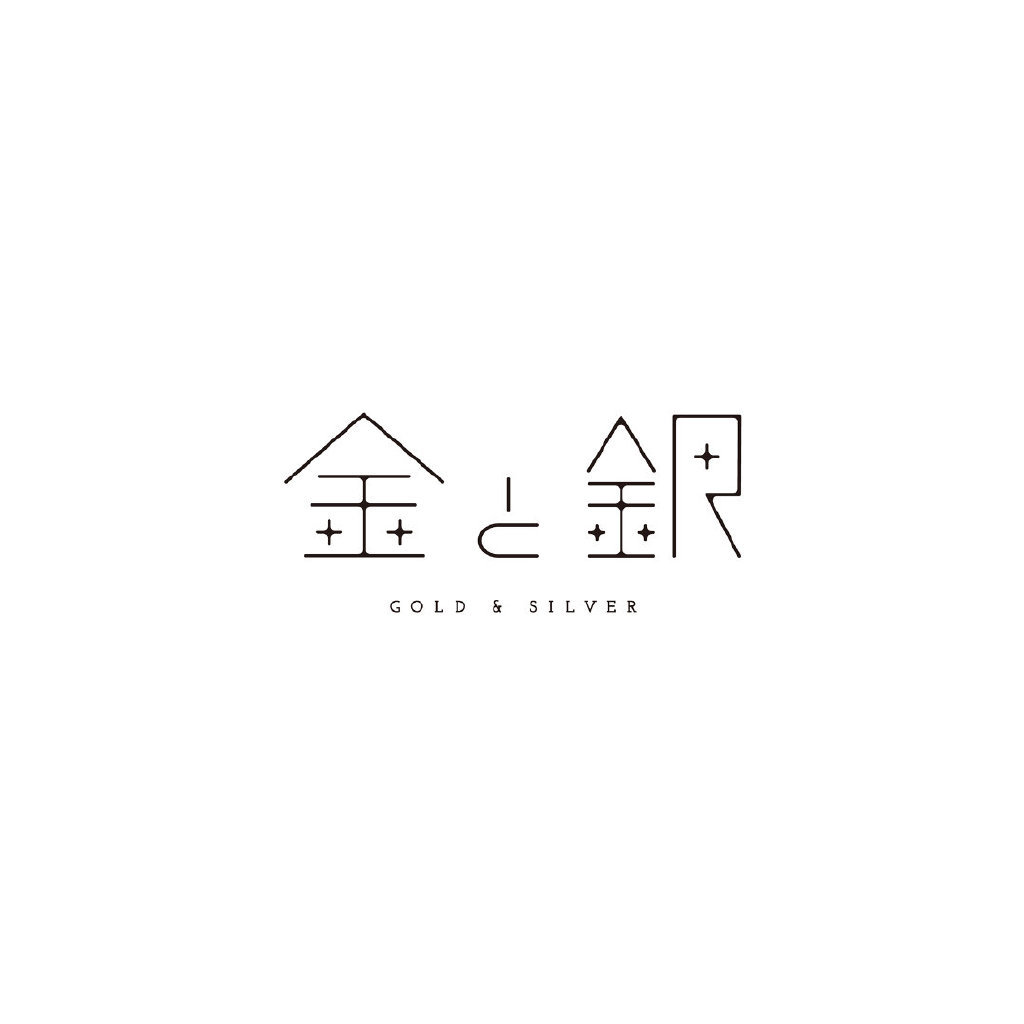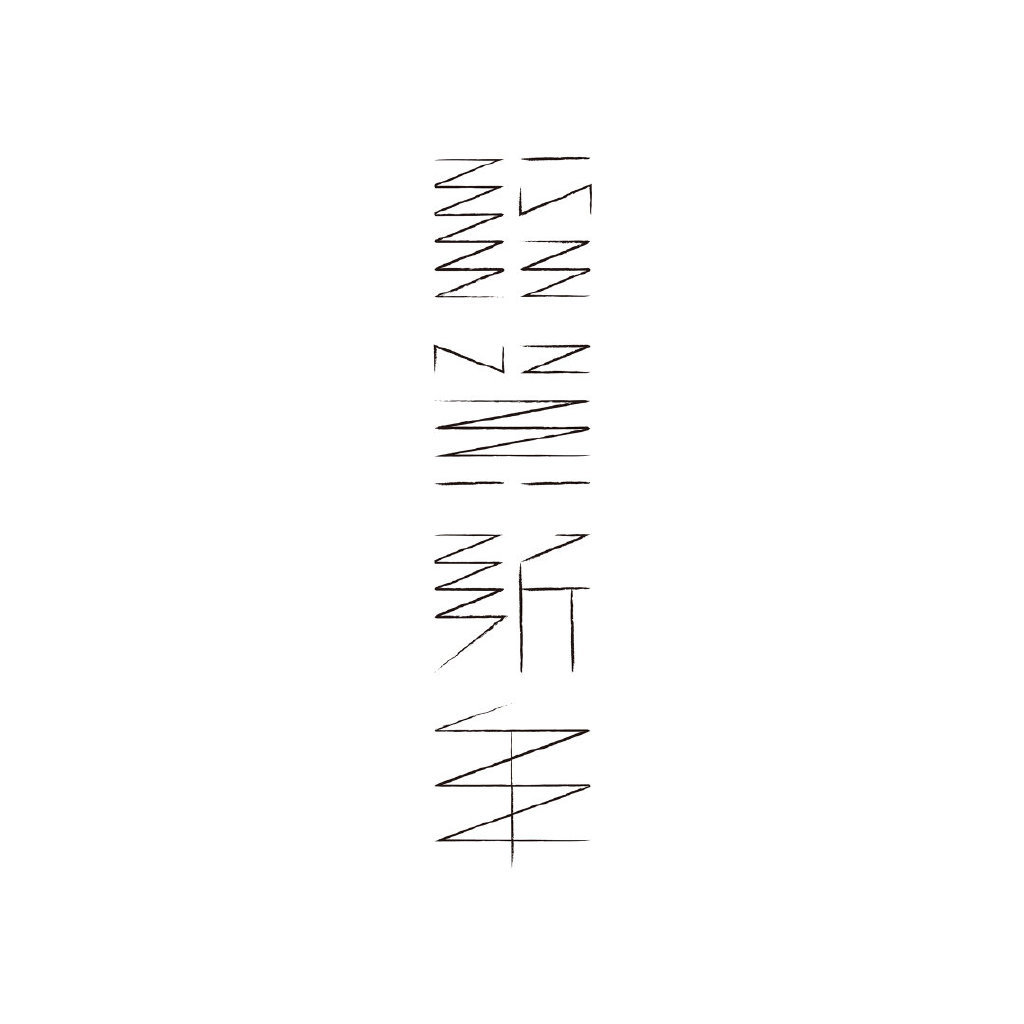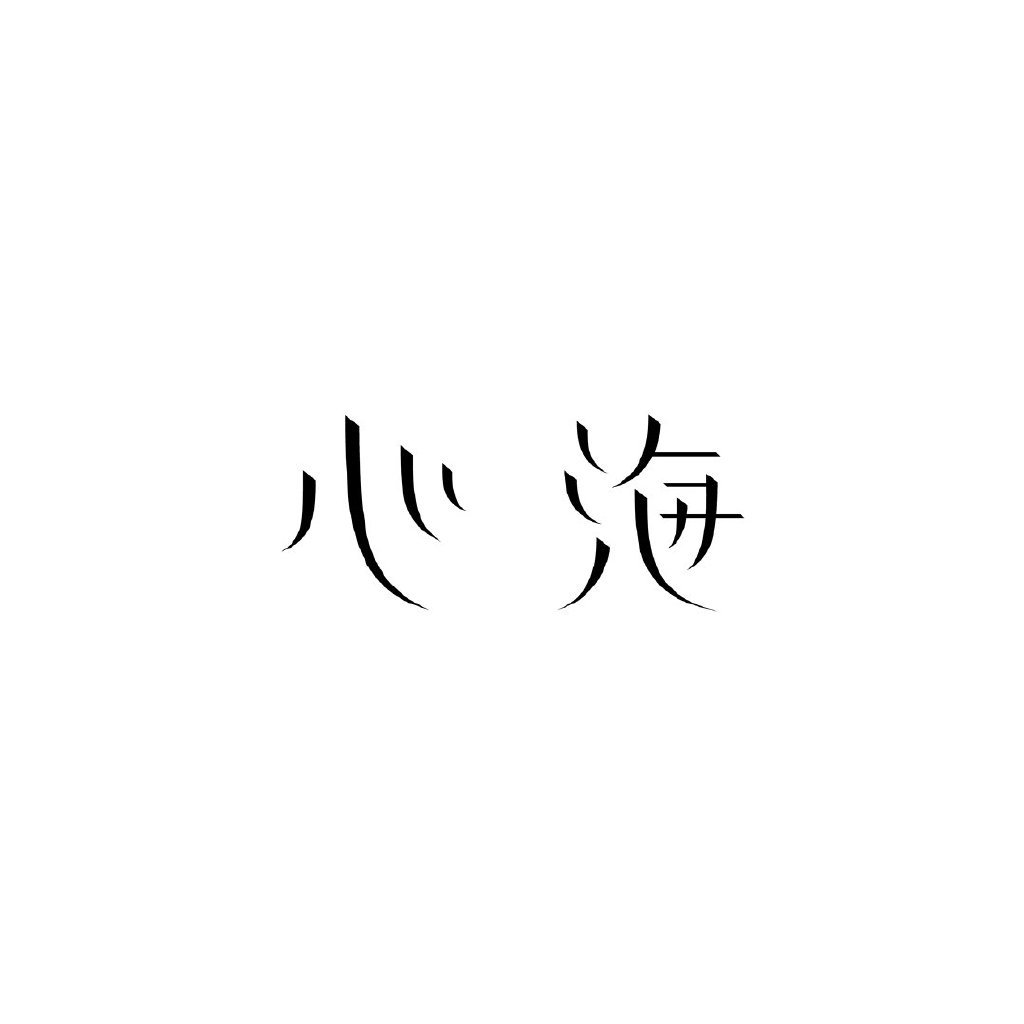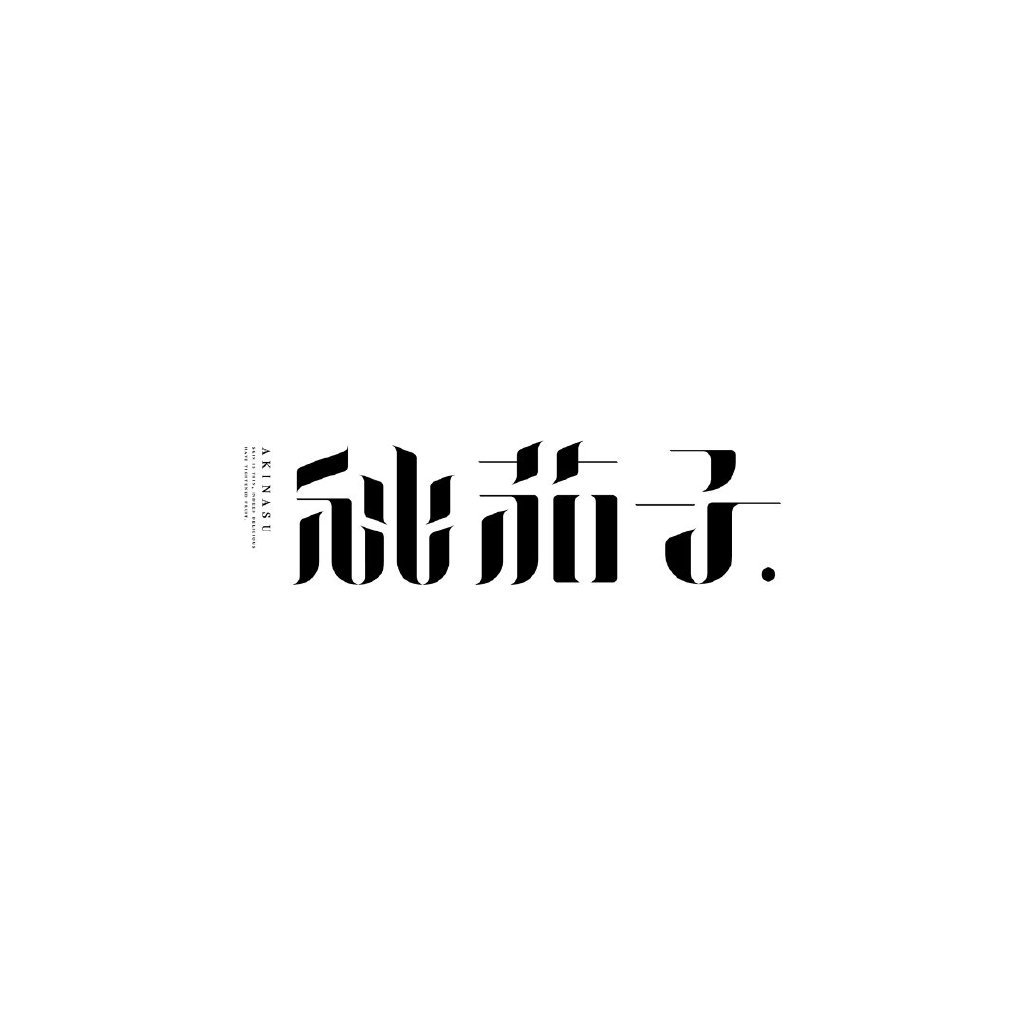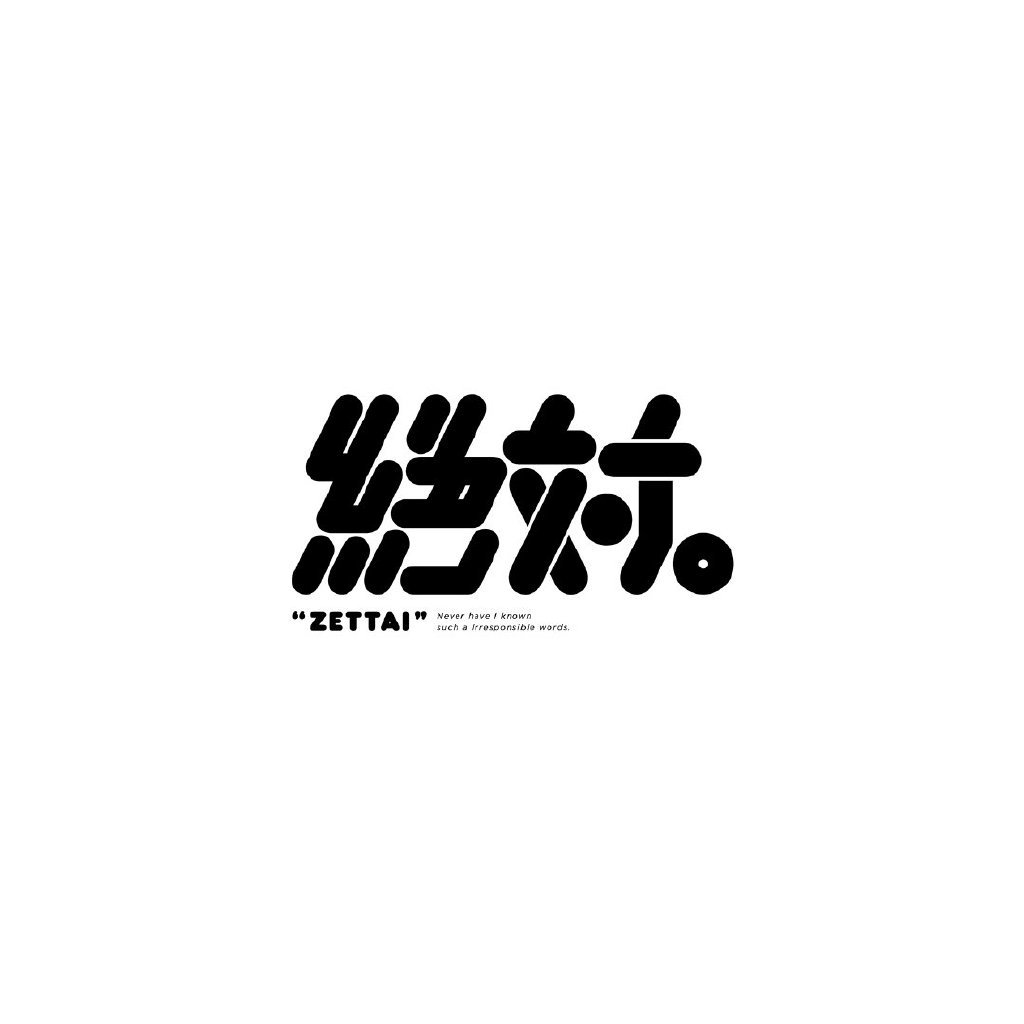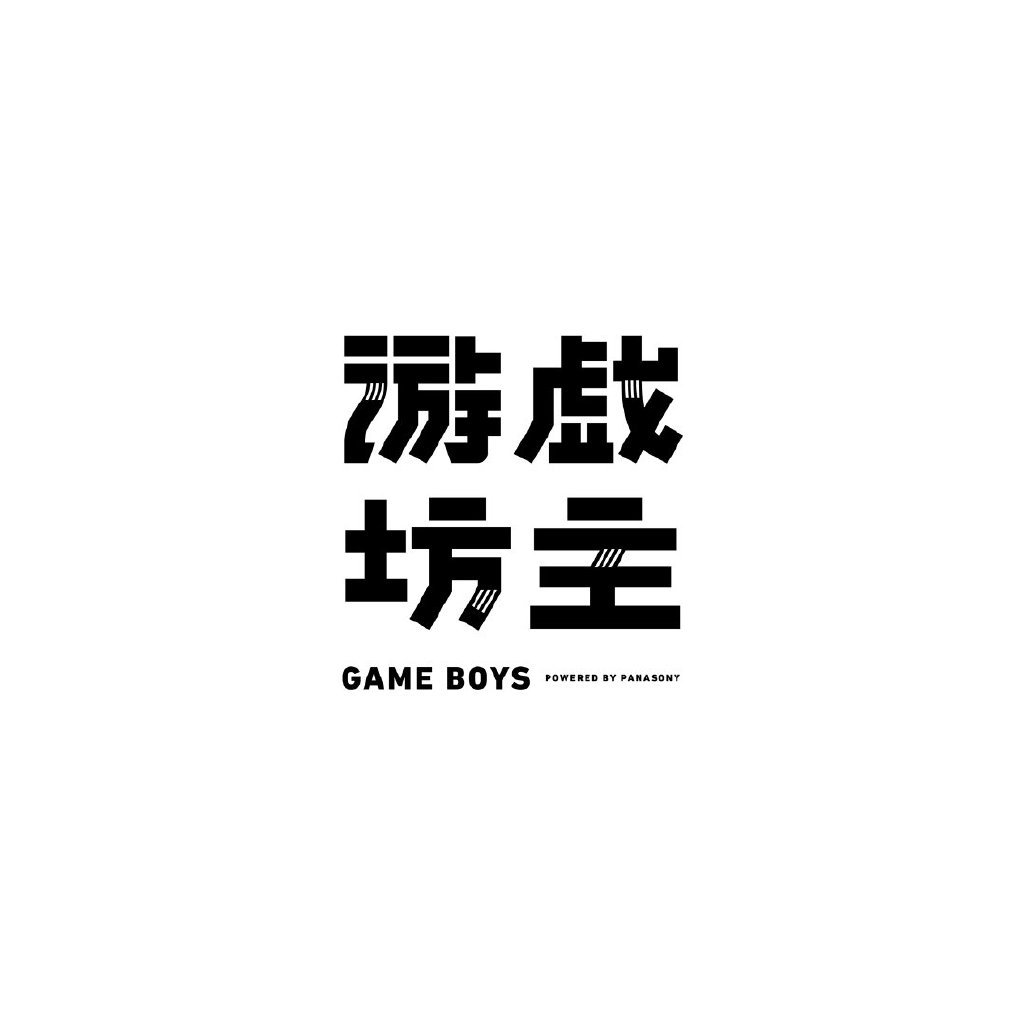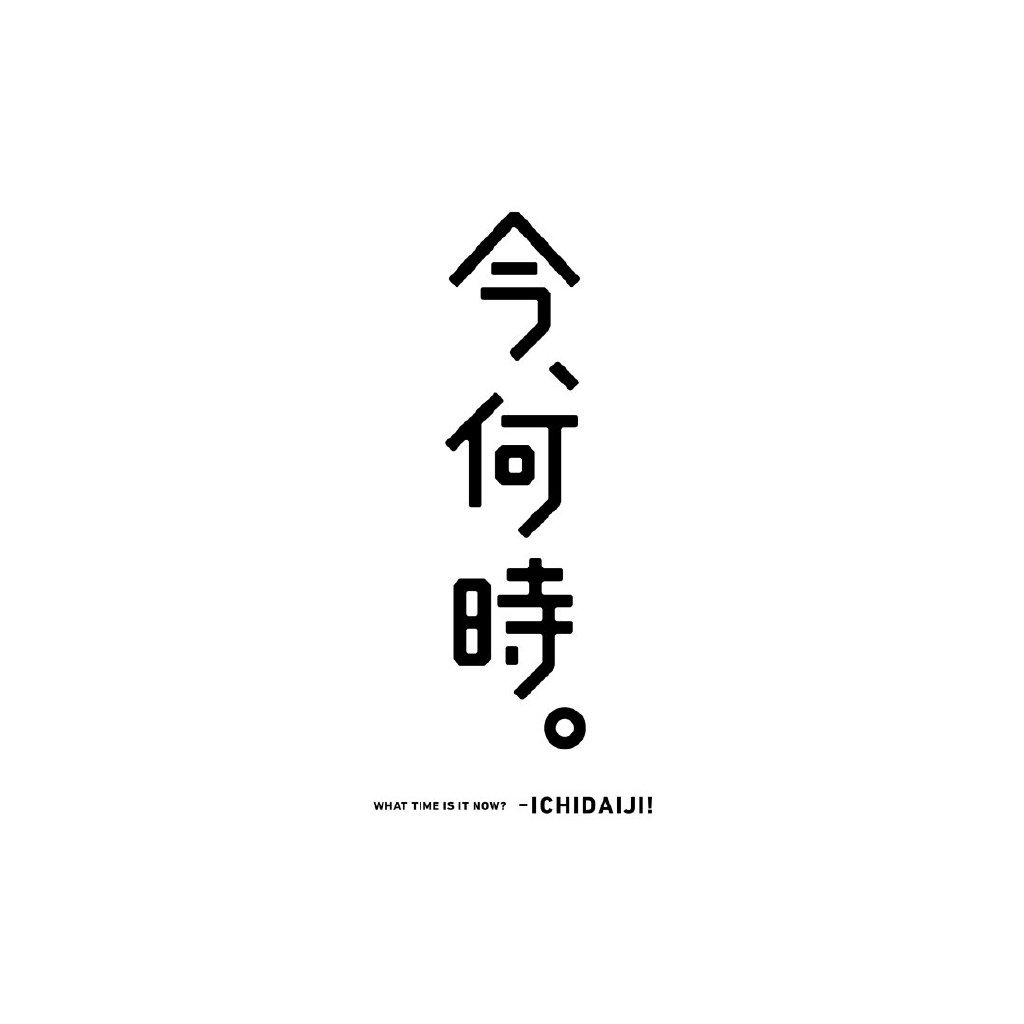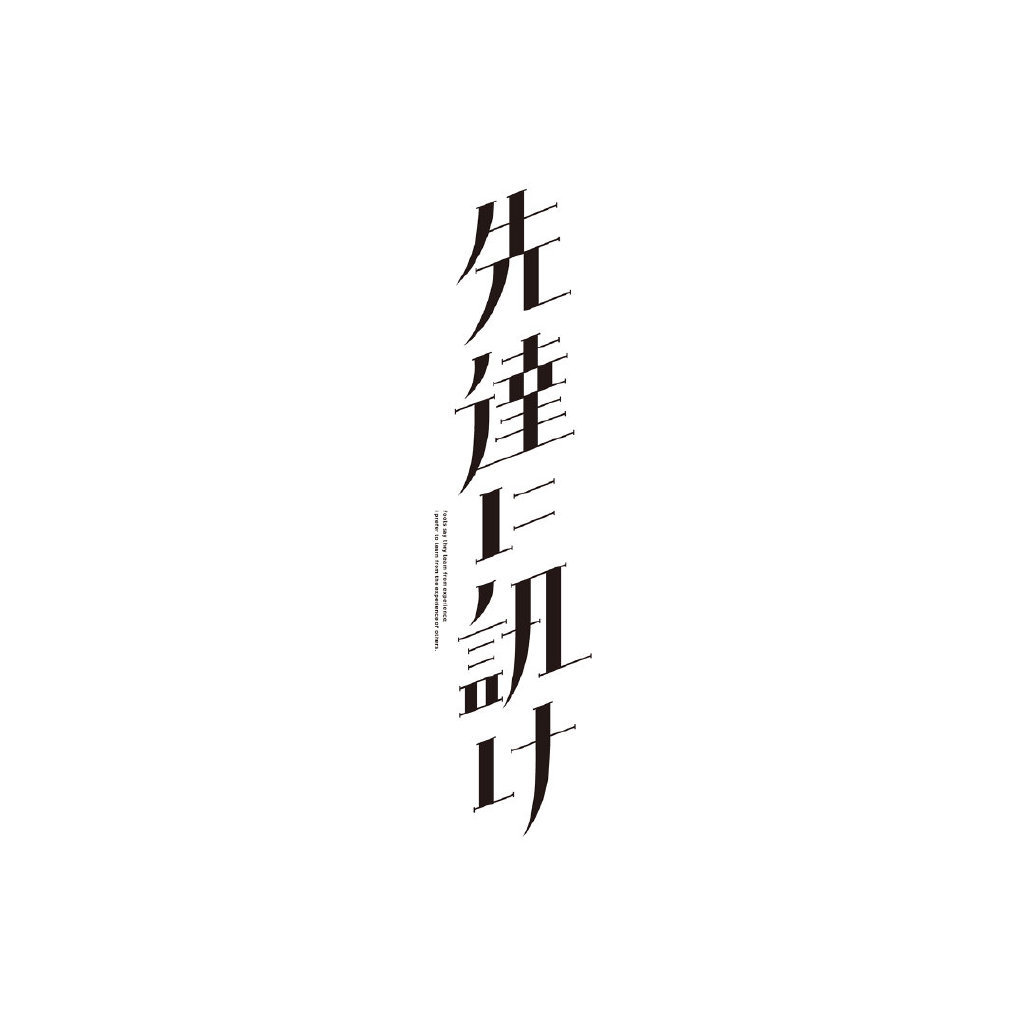
日本设计师 kisuke oota 的字体设计作品赏析
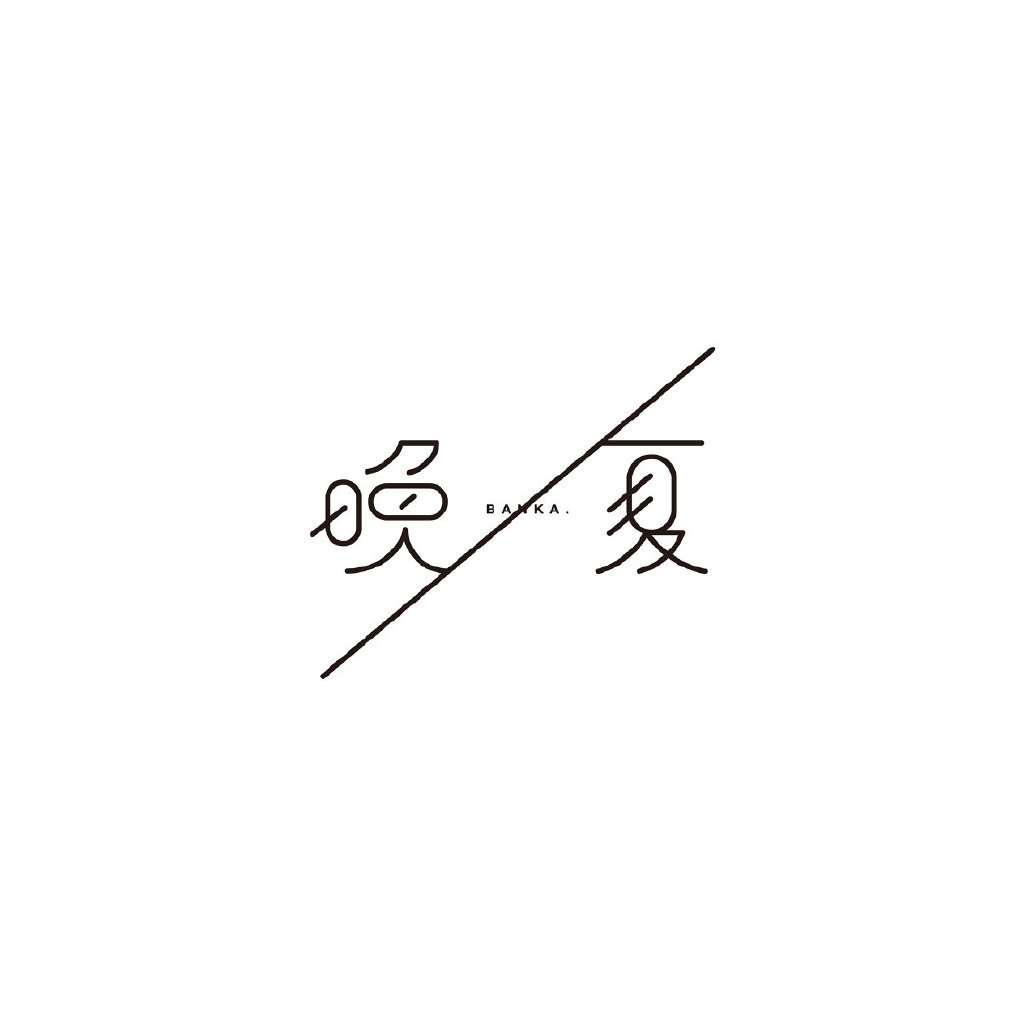
日本设计师 kisuke oota 的字体设计作品赏析,这款字体结构工整、笔画清晰,兼顾美观与易读性,适用于标题、正文、海报、包装、LOGO 等多种场景。字形优雅稳定,风格百搭耐看,适配日常排版与创意设计,让文字呈现更舒适、更具质感。日本设计师 kisuke oota 的字体设计作品赏析一笔一画,皆是细节,以均衡的比例、流畅的线条打造舒适视觉体验,字形端正大气,风格简约现代。无论是商业设计、品牌宣传还是日常排版,都能轻松驾驭,让文字更有格调与力量。日本设计师 kisuke oota 的字体设计作品赏析字体下载。